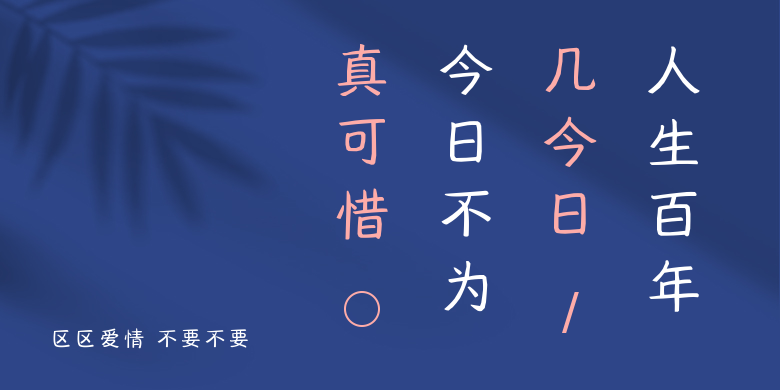
区区爱情 不要不要
区区爱情 不要不要,这款字体结构工整、笔画清晰,兼顾美观与易读性,适用于标题、正文、海报、包装、LOGO 等多种场景。字形优雅稳定,风格百搭耐看,适配日常排版与创意设计,让文字呈现更舒适、更具质感。区区爱情 不要不要一笔一画,皆是细节,以均衡的比例、流畅的线条打造舒适视觉体验,字形端正大气,风格简约现代。无论是商业设计、品牌宣传还是日常排版,都能轻松驾驭,让文字更有格调与力量。区区爱情 不要不要字体下载。